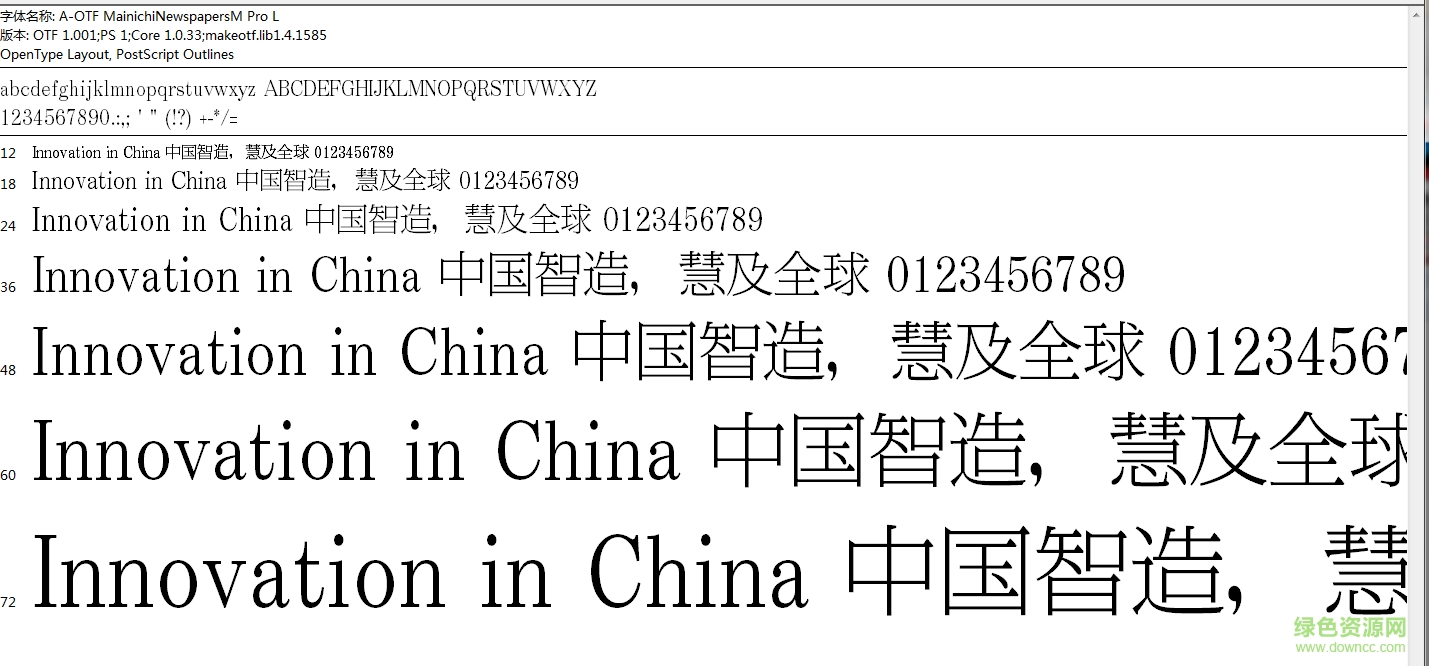
新闻明朝体是一款好用的繁体字体,字体非常的工整,笔画纤细,非常的秀气,与一般报纸杂志的字体比较类似,欢迎喜爱的朋友到绿色资源网下载体验!
新闻明朝体是指宋体字在日本的称呼,在台湾和韩国也有明朝体的叫法。汉字的计算机Font技术最初由日本开发,传至台湾,台湾沿用了日本明朝体的称呼。
《每日新闻》是日本非常普遍的一份报纸,也是日本历史最悠久的报纸,每日新闻明朝体时一款非常适合做标题的字体,字体结构非常不错,用来设计LOGO字体也是不错